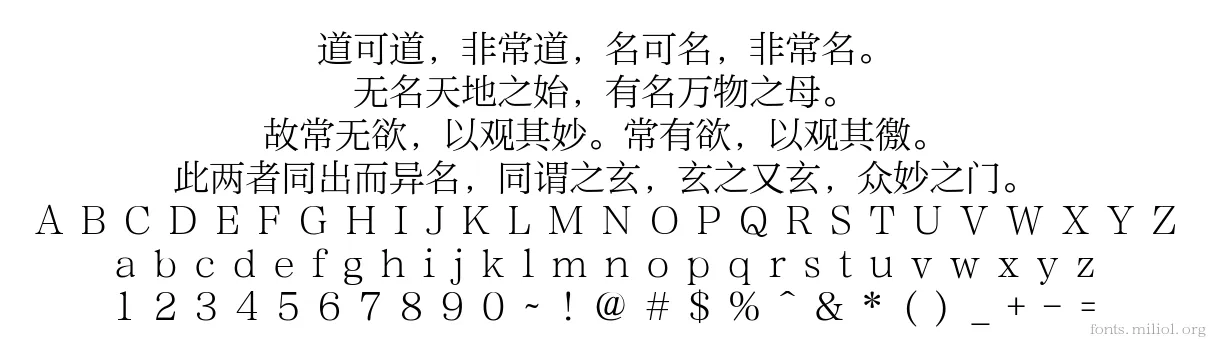
**方正纤雅宋_GBK:一款优雅的中文印刷字体**
方正纤雅宋_GBK(FZYaSong-EL-GBK)是方正字库推出的一款兼具传统宋体韵味与现代设计美感的印刷字体。其设计灵感源于经典宋体的骨架结构,同时通过纤细的笔画和柔和的曲线,赋予文字轻盈雅致的视觉体验。该字体属于GBK编码字符集,支持繁简体中文及多种符号,适用于书籍排版、杂志设计、广告宣传等场景。
纤雅宋的笔画处理尤为精细,横竖比例协调,转折处圆润流畅,既保留了宋体的端庄感,又避免了传统宋体的厚重感。其“EL”(Extra Light)字重特性使整体风格清新简约,尤其适合长篇文本的阅读,能有效减轻视觉疲劳。此外,该字体在屏幕显示和印刷输出中均表现稳定,清晰度高,适配多种媒介需求。
作为一款专业级字体,方正纤雅宋_GBK既满足了设计师对美学的追求,也兼顾了实用性与兼容性,是中文排版领域的优质选择之一。